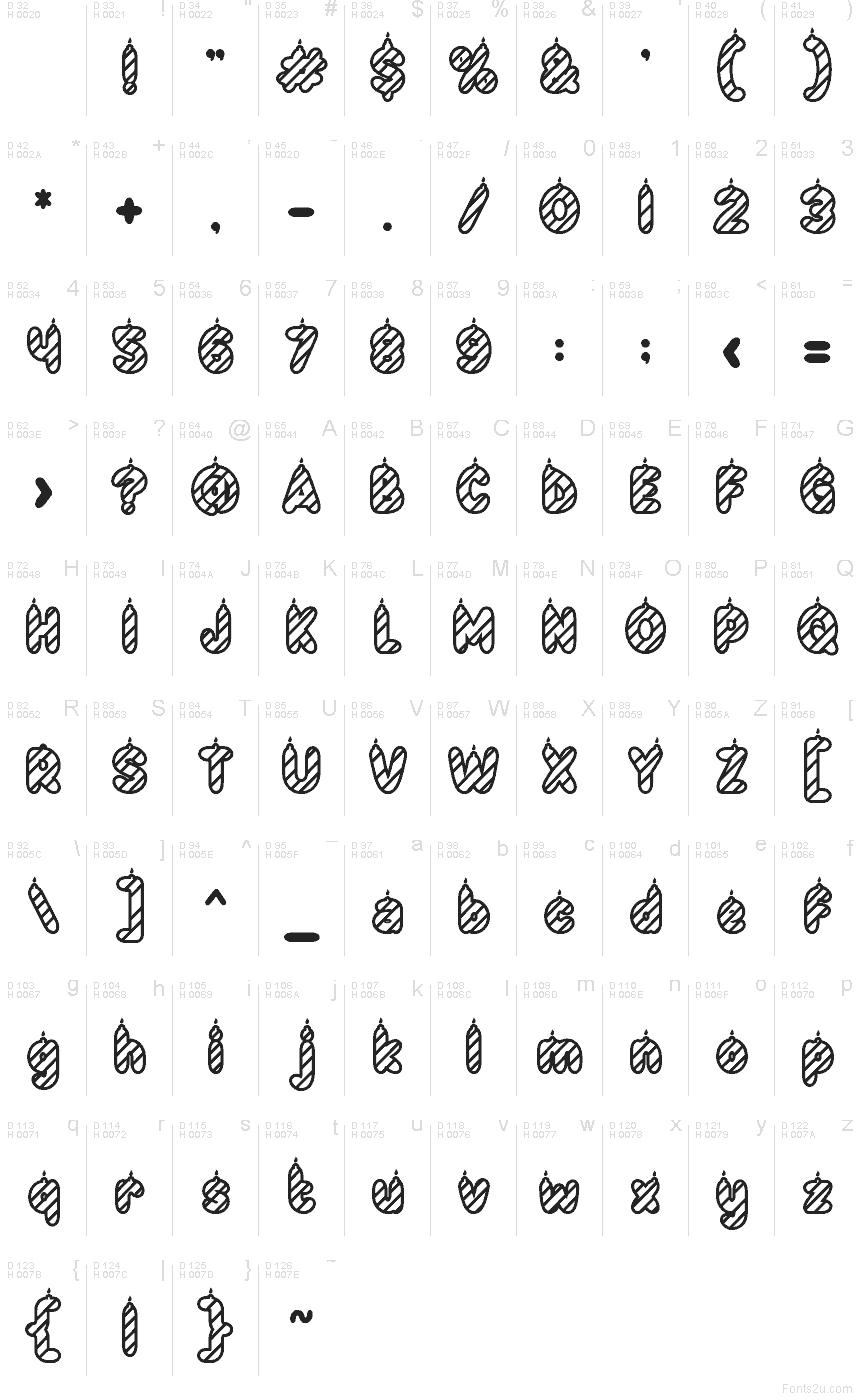
Cake Couture Five
Cake Couture Five von Putracetol Studio ist eine kostenlose Display-Schriftart, die aussieht, als wäre sie direkt mit Zuckerguss auf ein Bäckerei-Schaufenster aufgetragen worden. Die abgerundeten Formen, die gestreifte Füllung im Zuckerstangen-Look und die kleinen flammenartigen Akzente verleihen diesem Alphabet eine verspielte Patisserie-Ästhetik, die weit mehr nach Süßwarenladen als nach gewöhnlicher Deko aussieht.
Diese kostenlose Schriftart passt perfekt zu Bäckerei-Branding, Geburtstagseinladungen, Dessert-Verpackungen, Café-Menüs und Social-Media-Posts, bei denen kurze Wörter eine glasierte, festliche Note brauchen. Dank der weichen, ballonen Formen und der gestreiften Details funktioniert sie auch hervorragend für Cover, Titel und Monogramme – schon bei wenigen Buchstaben kommt das Thema wunderbar zur Geltung.